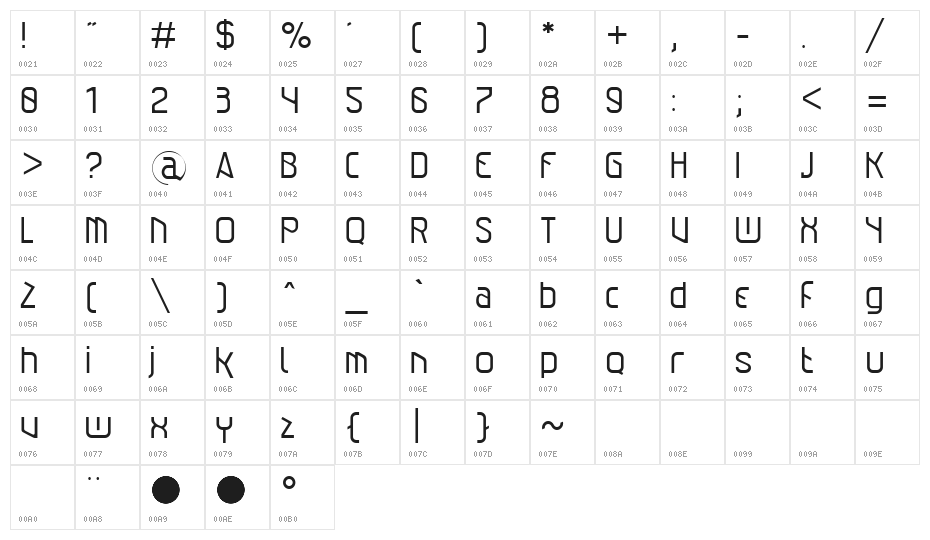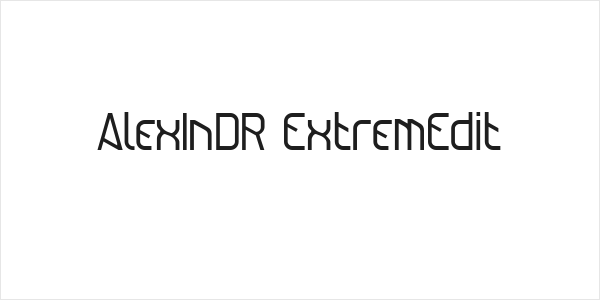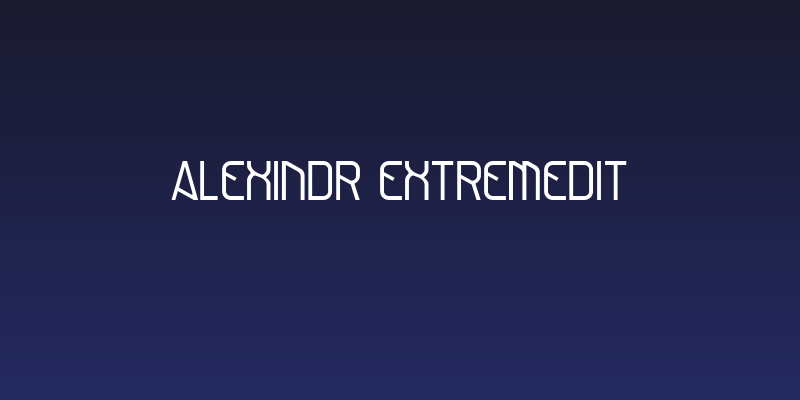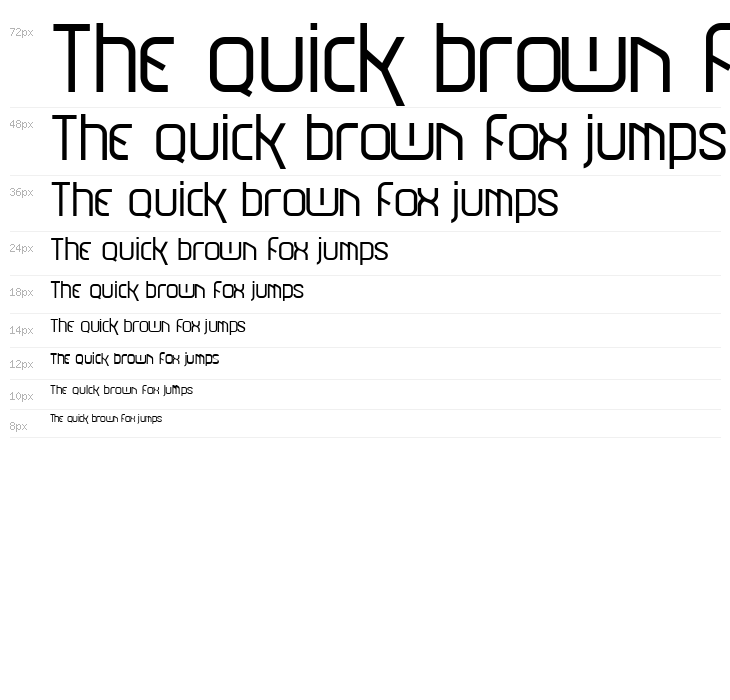
AlexInDR ExtremEdit Font
✎ Sci-fi
| Caso de uso | Headlines, Logos, Digital Interfaces |
| Proyectos propuestos | Ideal for technology branding, modern advertising, digital interfaces, and innovative product packaging. |